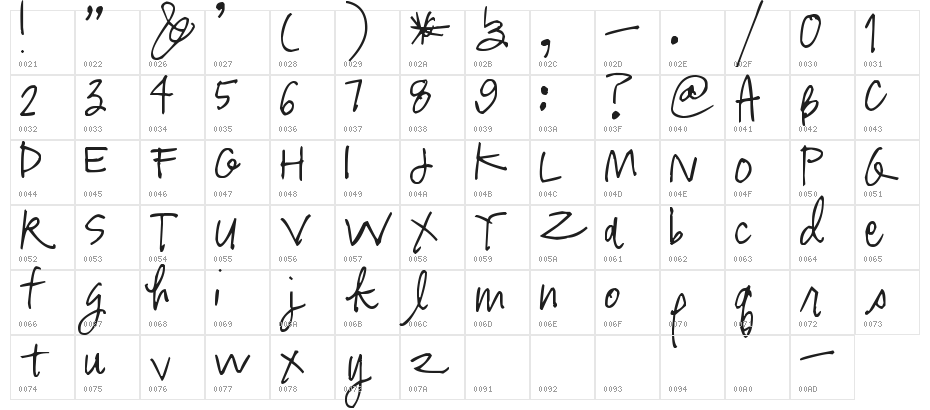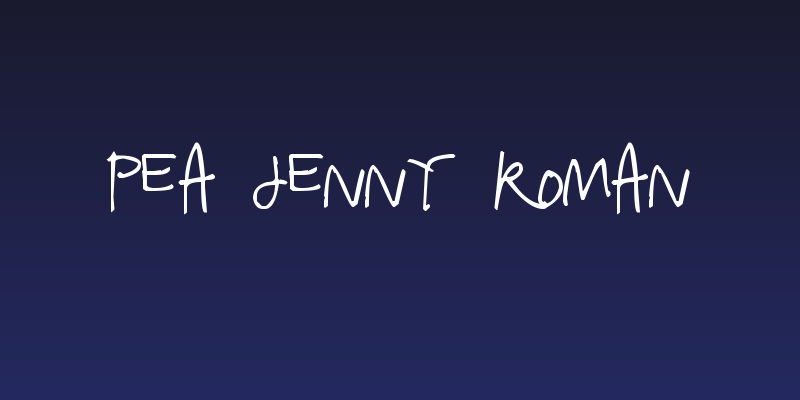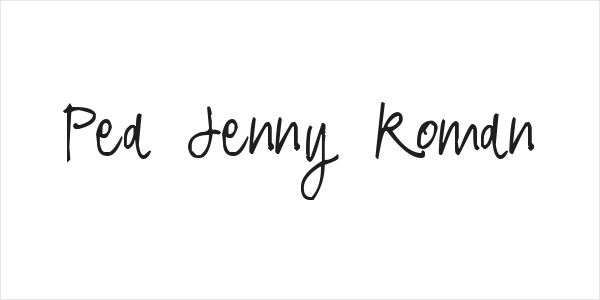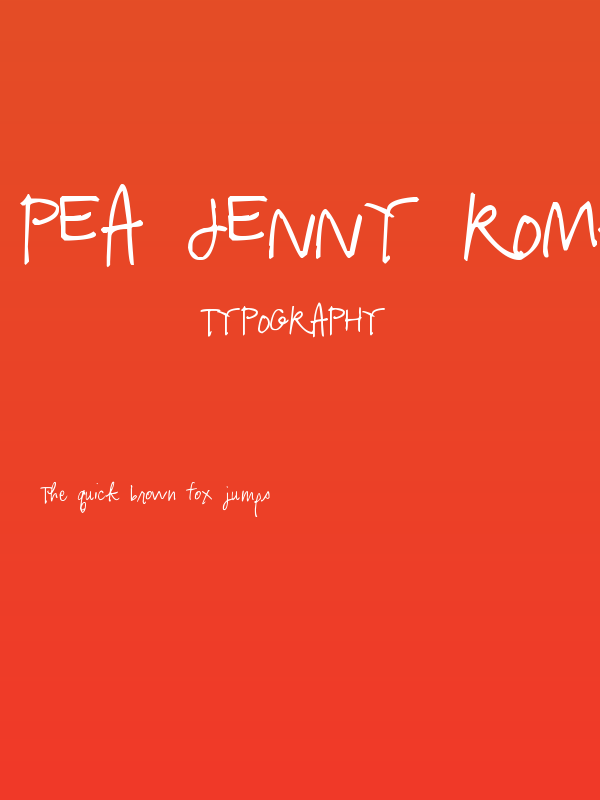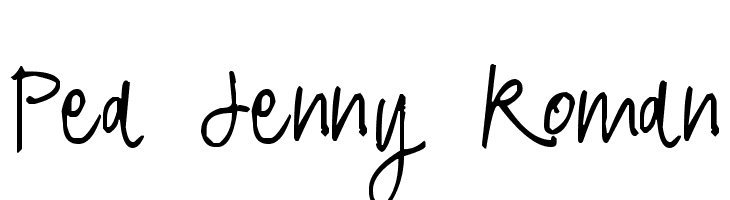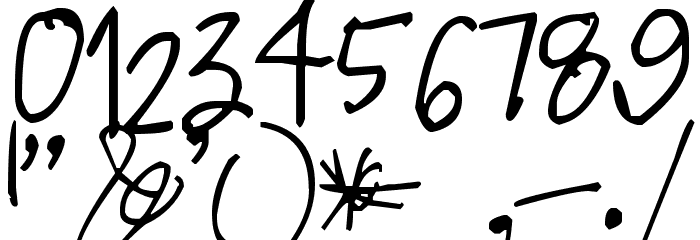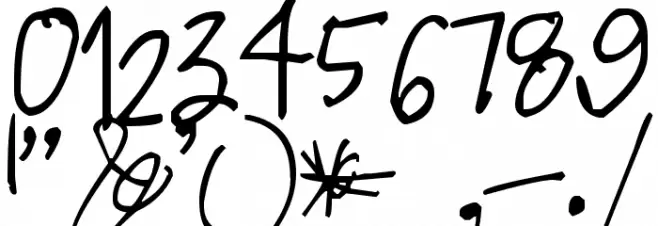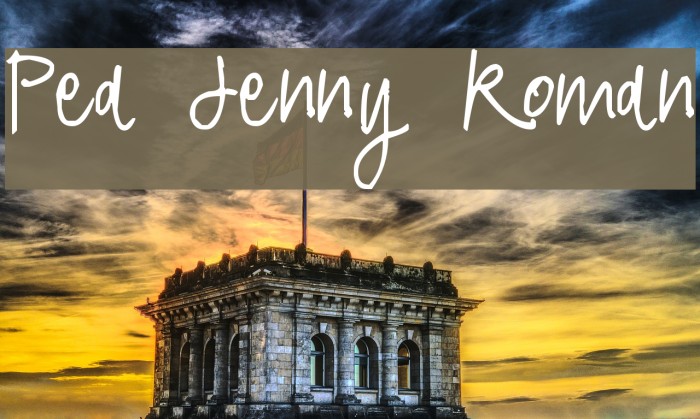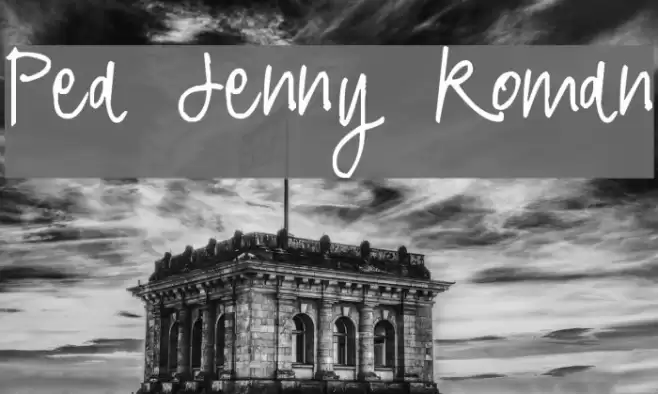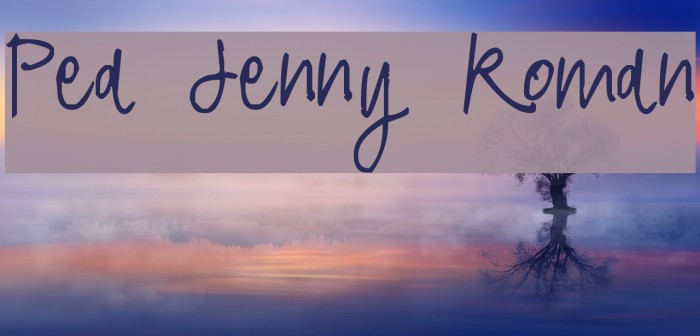
Pea Jenny Roman Font
| Stile generale | Casual |
| Caso d'uso | Logos, Greeting cards, Informal invitations |
| Progetti proposti | Ideal for personal notes, greeting cards, informal invitations, and creative branding projects. |